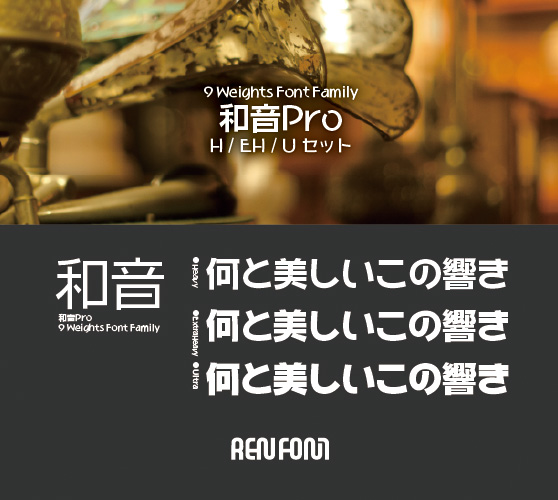
和音Pro-タイトル・大見出し用3ウェイトセット(H/EH/U)
WaonPro-H,WaonPro-EH,WaonPro-U
「日本タイポグラフィ年鑑2005」入選作「和音」を源流とし、タイプデザイナー金井和夫が2年以上の期間をかけて制作した渾身の労作。それぞれの字種に音楽的特徴を持たせ、文章として連なった時にメロディーのような彩りを演出します。タイトル・大見出し用の3ウェイトセット。